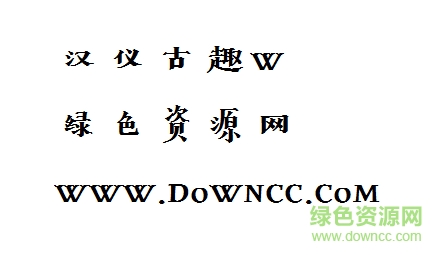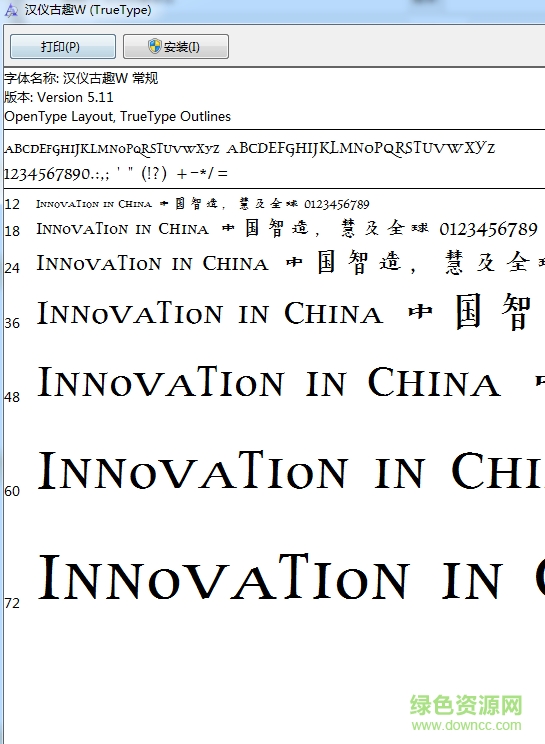
漢儀古趣w字體是一款非常好看的古典趣味字體,古趣體看似雜亂無(wú)章不整齊,實(shí)則字里筆畫透露著非常頑皮的古代氣息,感興趣就到綠色資源網(wǎng)下載吧!
漢儀古趣字體非常的優(yōu)雅脫俗,字體大小風(fēng)格不一,整體效果十分滑稽,特別有創(chuàng)意,喜歡就到綠色資源網(wǎng)下載使用吧!